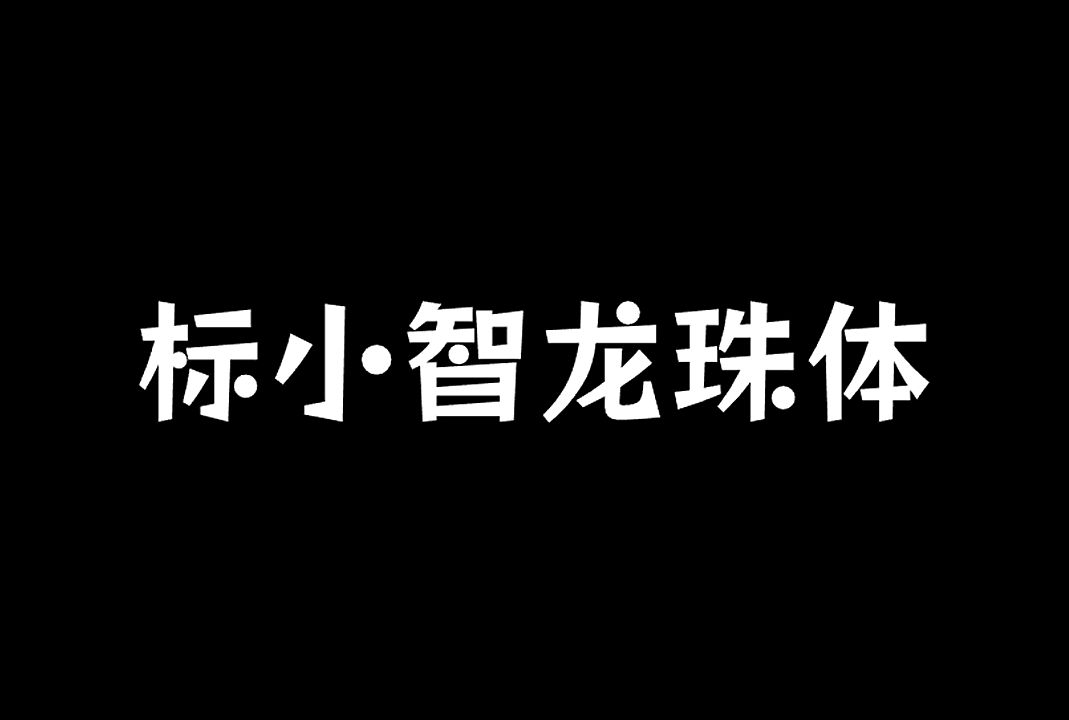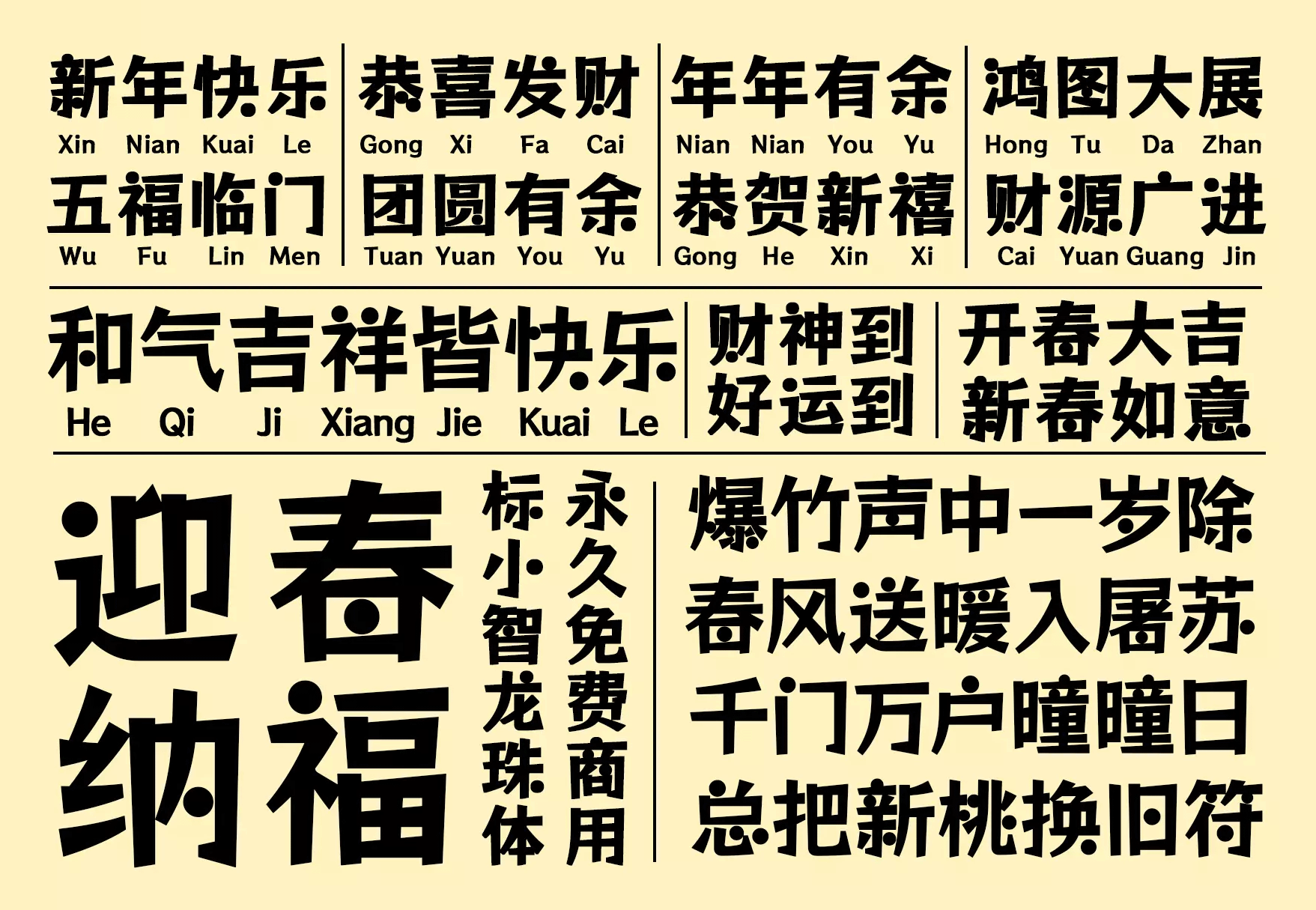
标小智龙珠体是标小智公司携手猫啃网共同推出的第二款免费商用中文字库,首款免费商用字体标小智无界黑于2022年发布。
标小智龙珠体是基于日本著名字体设计公司Fontworks免费开源的摇滚乐 One(日文名:ロックンロール)字体进行简体字补充的一款字体。标小智龙珠体是一款卡通风格字体,字体风格动感活泼俏皮可爱,非常适合用在卡通类logo设计中;该字体用龙珠代替部分笔画,气质更加鲜明有记忆点,允许任何个人和企业免费使用,包括商用用途。